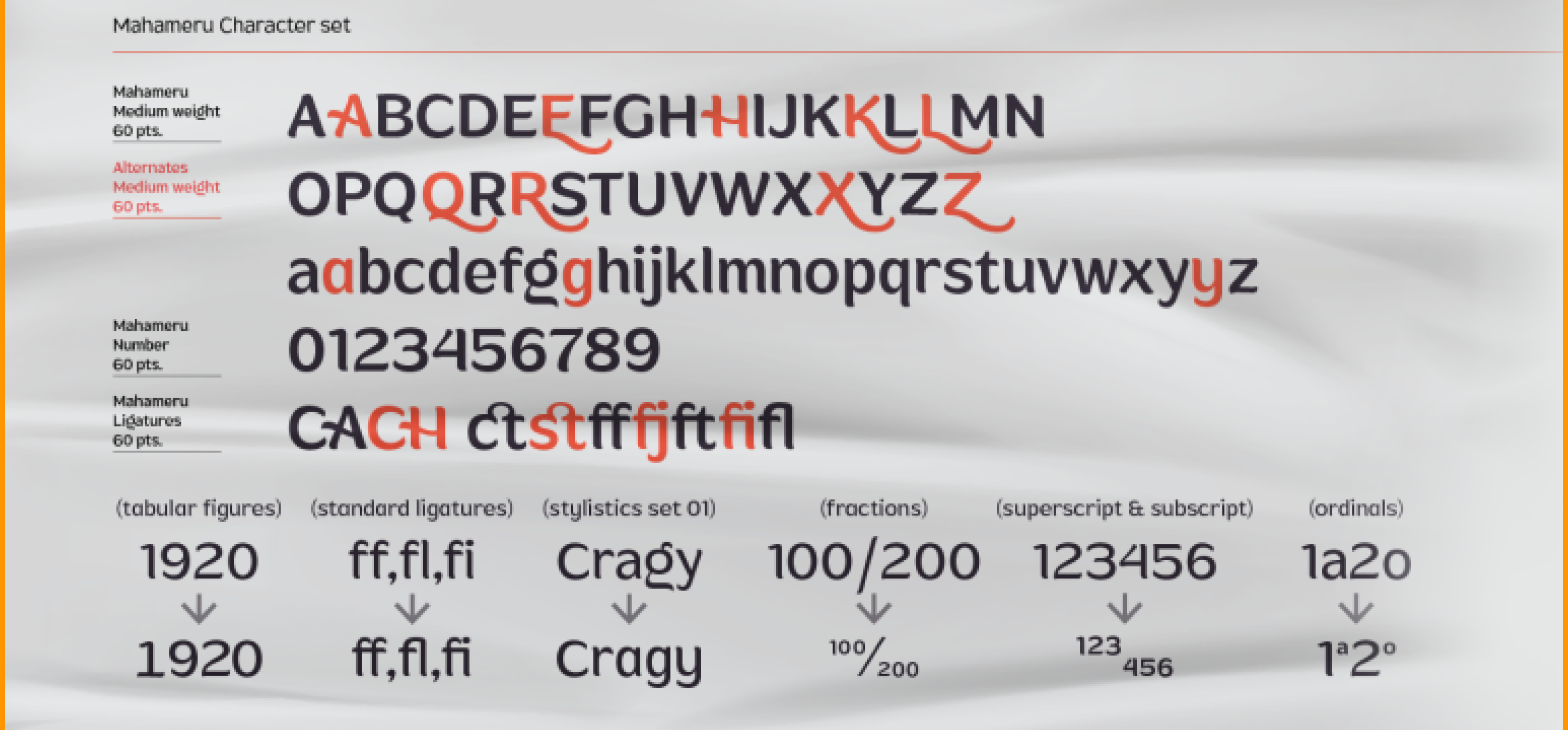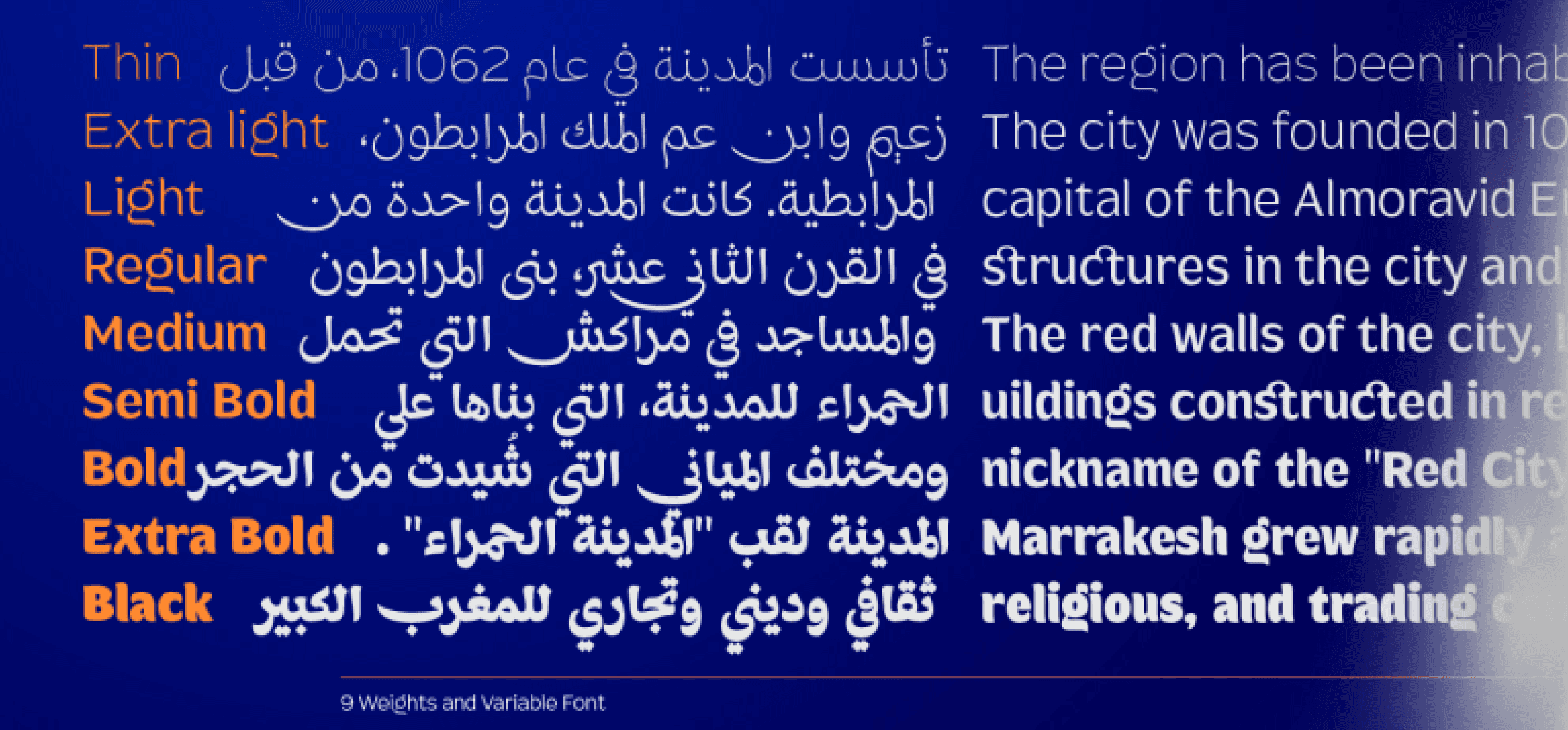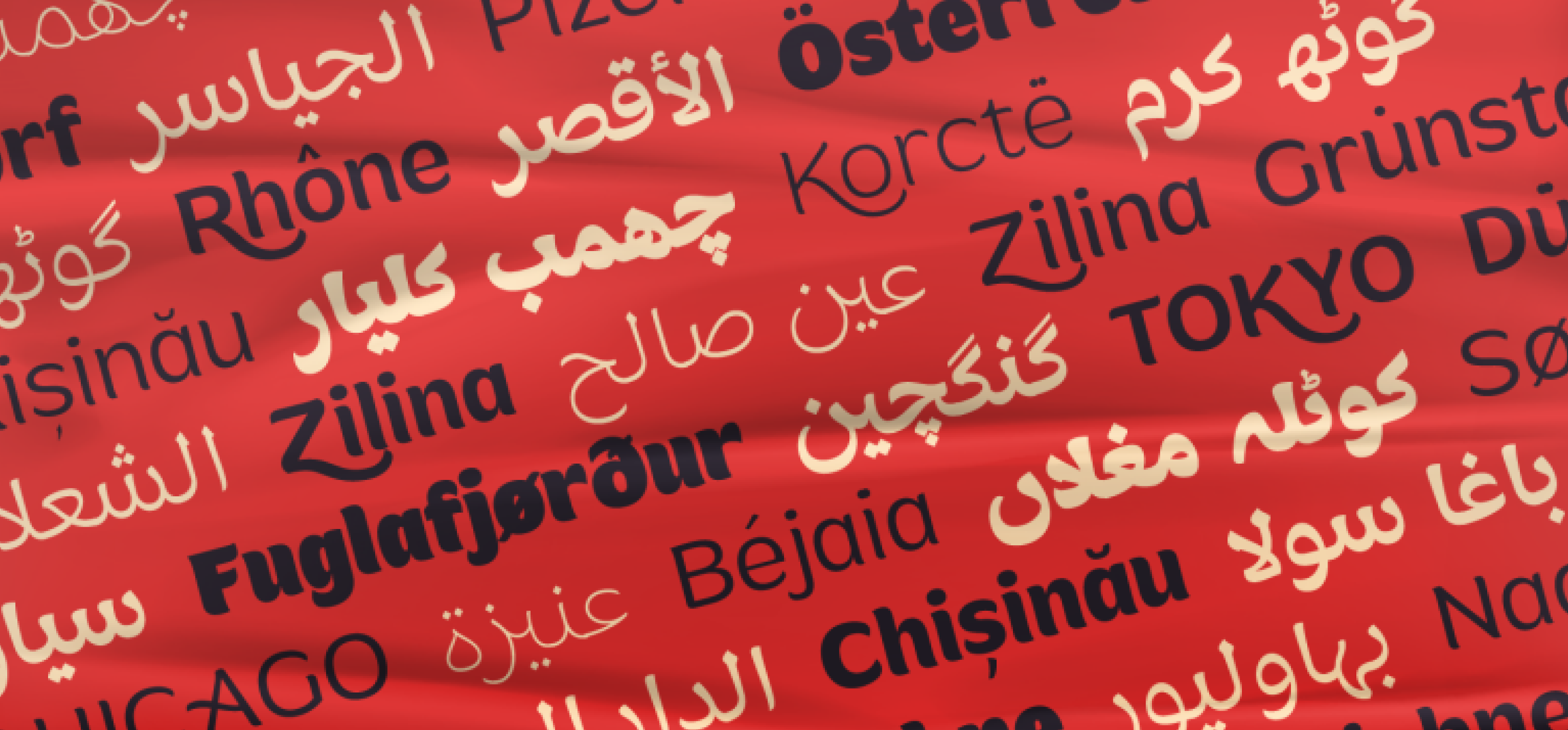
خط Mahameru Arabic هو النسخة العربية من خط Mahameru، ويتضمن محارف مخصصة للغات العربية، الأوردو، والفارسية.
يحتفظ الخط بطابعه المتين والناعم في آنٍ واحد، مع نهايات دقيقة في الضربات المستقيمة والمنحنية.
تتألف عائلة الخط من 9 أوزان تتراوح من الخفيف جدًا (Thin) إلى الثقيل جدًا (Black)، وتوفر مرونة كبيرة في الخصائص التصميمية، مما يساعدك في اختيار اللون الطباعي الأنسب لمشروعك.